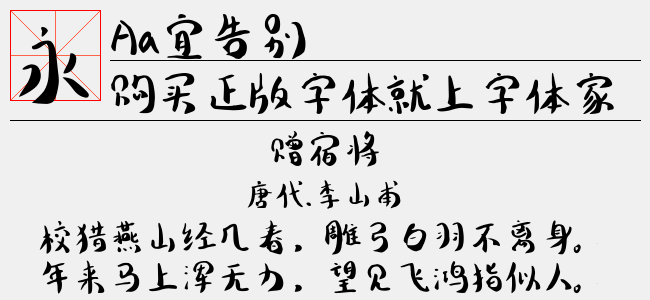
Aa宜告别(5.20 MTTF中文字体下载)
Aa宜告别 字体大小5.20 M,包含了6763个汉字以及附加其他英文字体和阿拉伯数字,属于Aa字体。Aa宜告别(TTF)可以免费下载,商业用途请自行购买版权,它的特征就是个性,变形,海报,书法,采用安装嵌入的安装方式,支持符号拉丁文日文中文等语言
字体作者:Aa字体
字体名称:Aa宜告别